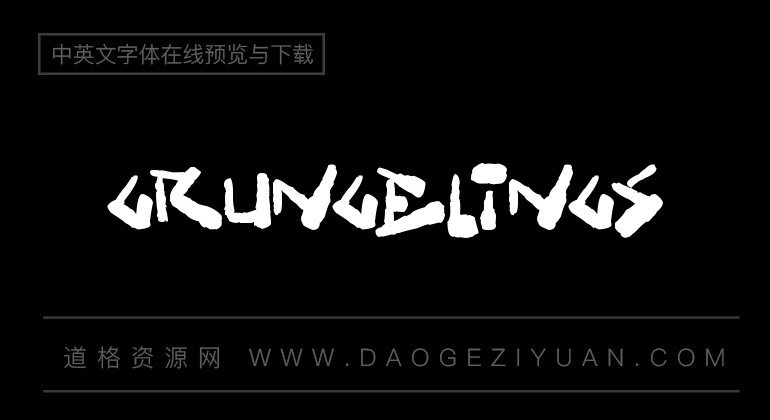
Grungelings
? Grungelings是一款受到80年代潮流影响的粗体字体,它具有强烈的时尚感和未来感,以及独特的复古风格。它的字体特点是大量的轮廓,添加了一些折痕和折痕,以及一些不规则的斜体,使其具有独特的外观。它适合用于广告,海报,品牌标识,电影海报,标题,标签,标题,网页,书籍和书籍封面等。
Grungelings是一款非常不错的手写艺术字体,具有很好的视觉感,适合于文化类的宣传设计、商业类品牌的广告和产品包装设计以及个性化文字排版等较多场景。